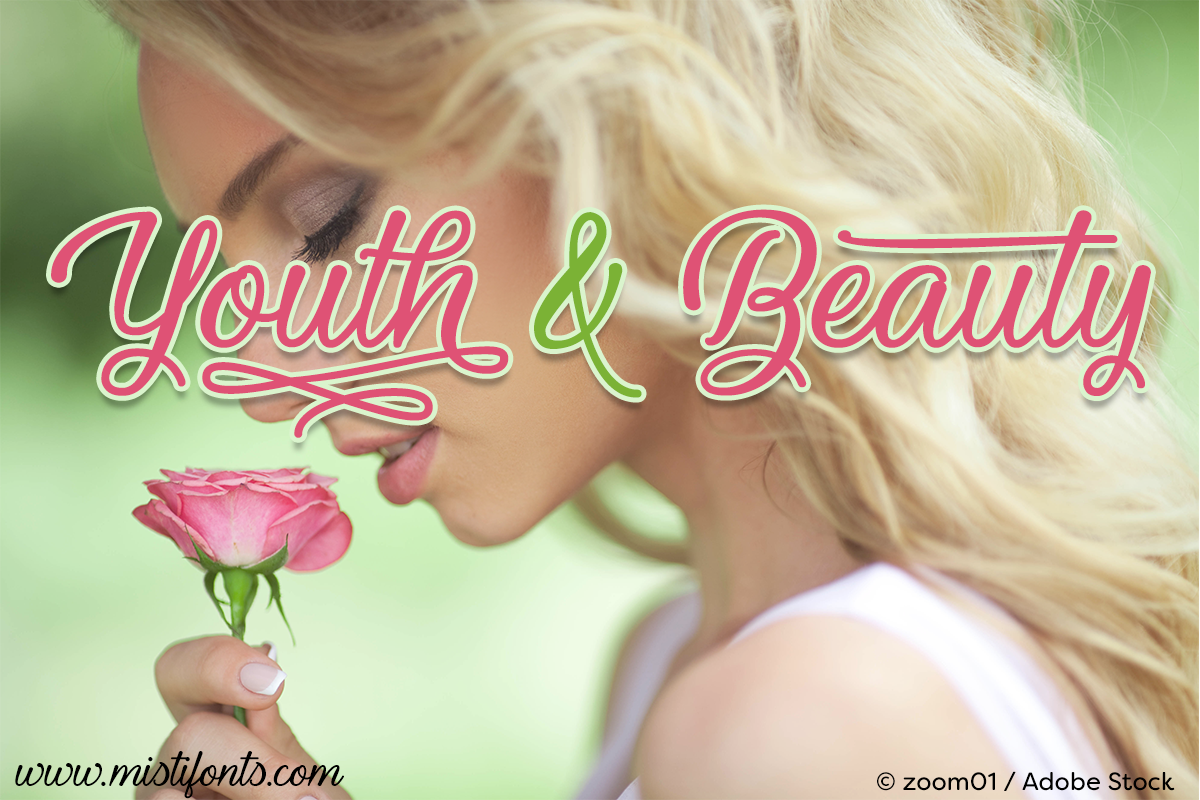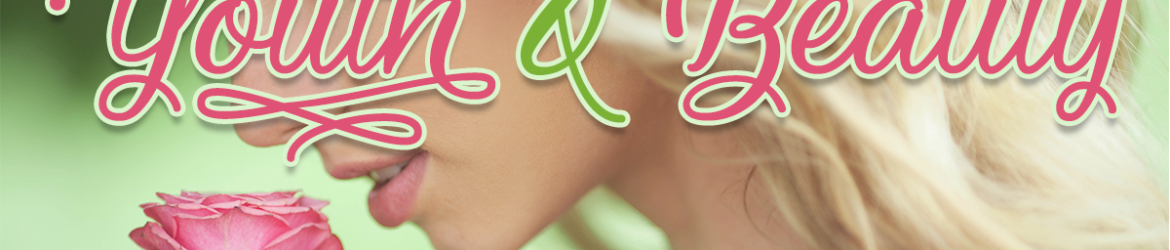
Youth and Beauty Font – Download Grátis
A fonte Youth and Beauty é perfeita para quem busca uma mão-dupla elegante e versátil para trabalhos pessoais ou não lucrativos. Desenvolvida pelo designer Misti’s Fonts, esta font é ideal para textos agradáveis que refletem um tom jovial e despretensioso, combinando suavidade com graça. Se você está procurando uma font de escrita manual para aplicar em sua arte digital ou design gráfico, essa é uma ótima escolha. Seu formato livre e não lucrativo permite que use Youth and Beauty na sua produção artística sem precisar se preocupar com direitos autorais ou licenças. Independentemente da quantidade de trabalho que você faça com a font Youth and Beauty, lembre-se: caso decida vender produtos criados usando essa mão-dupla, é preciso adquirir uma licença. Essa fonte é perfeita para quem quer manter seus projetos pessoais e não lucrativos livres de qualquer comprometimento contratual ou de direitos autorais.